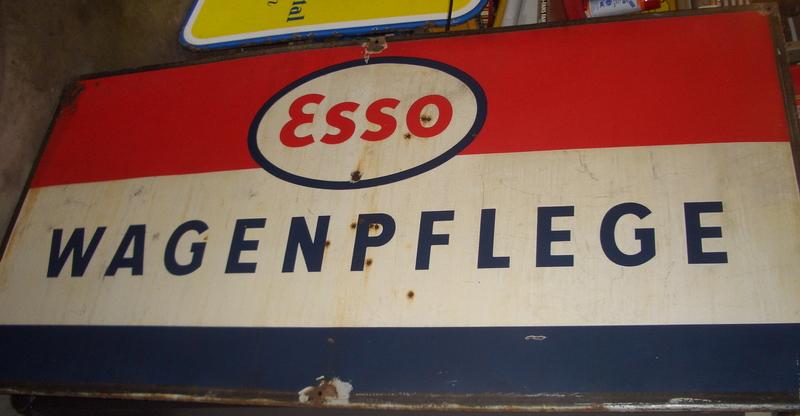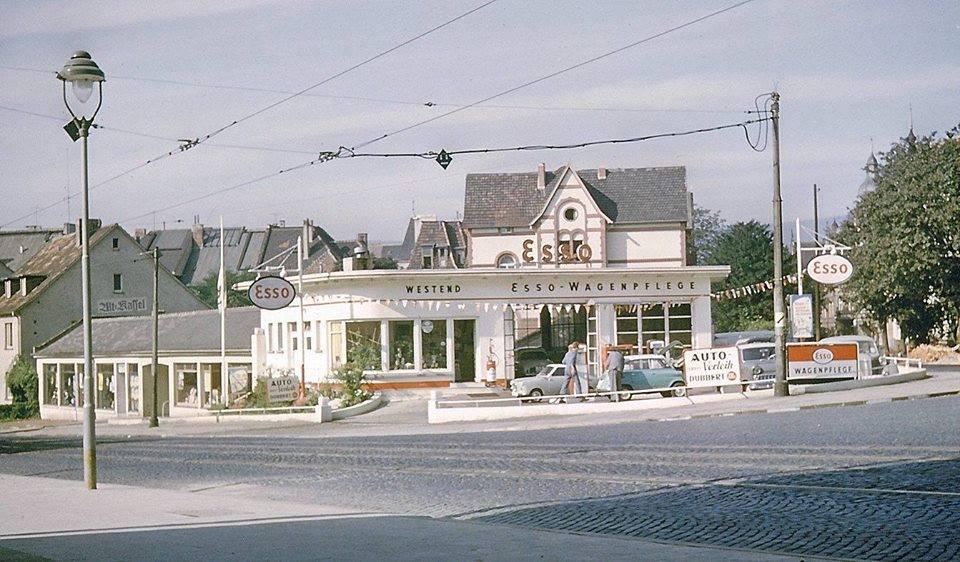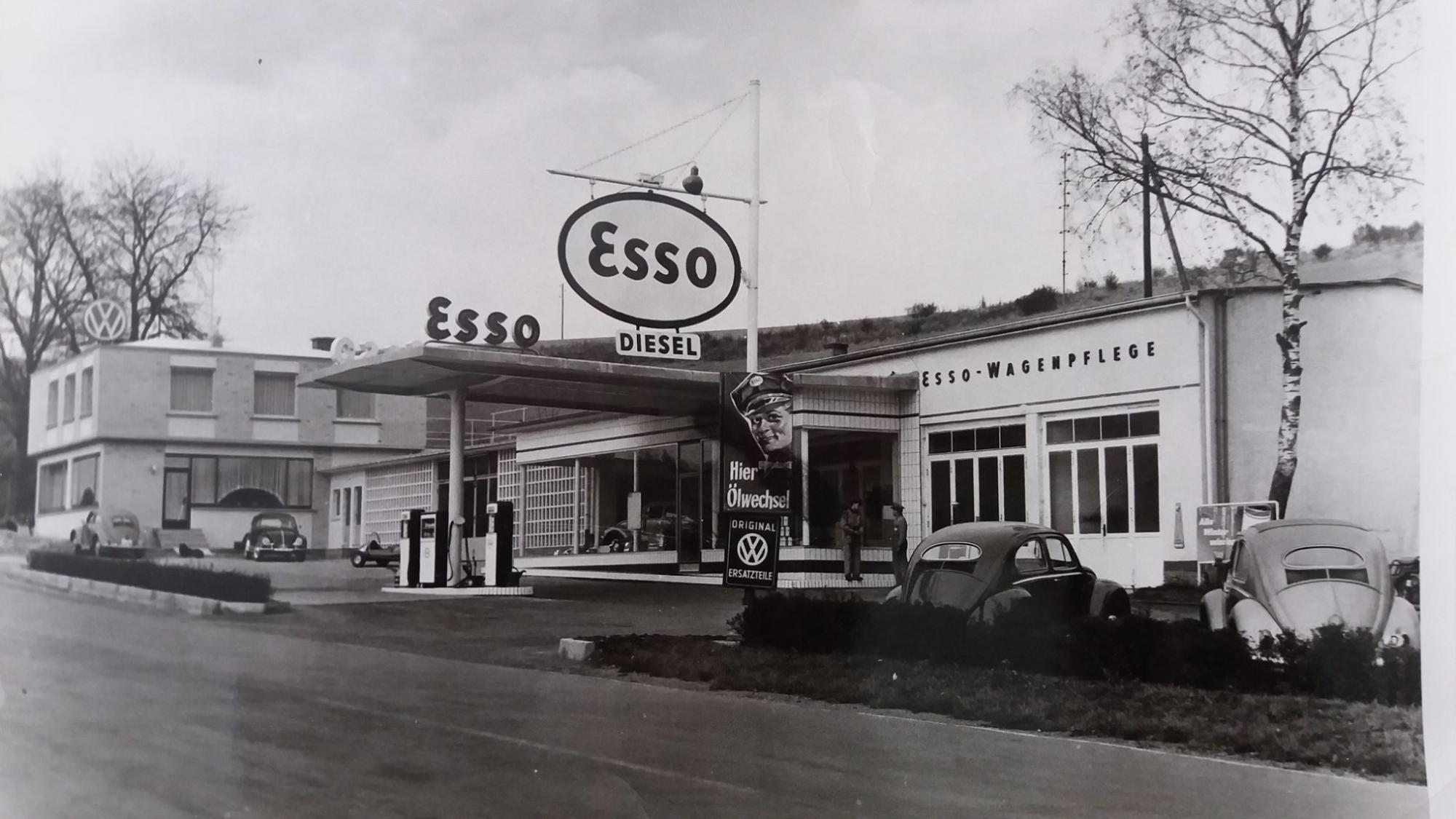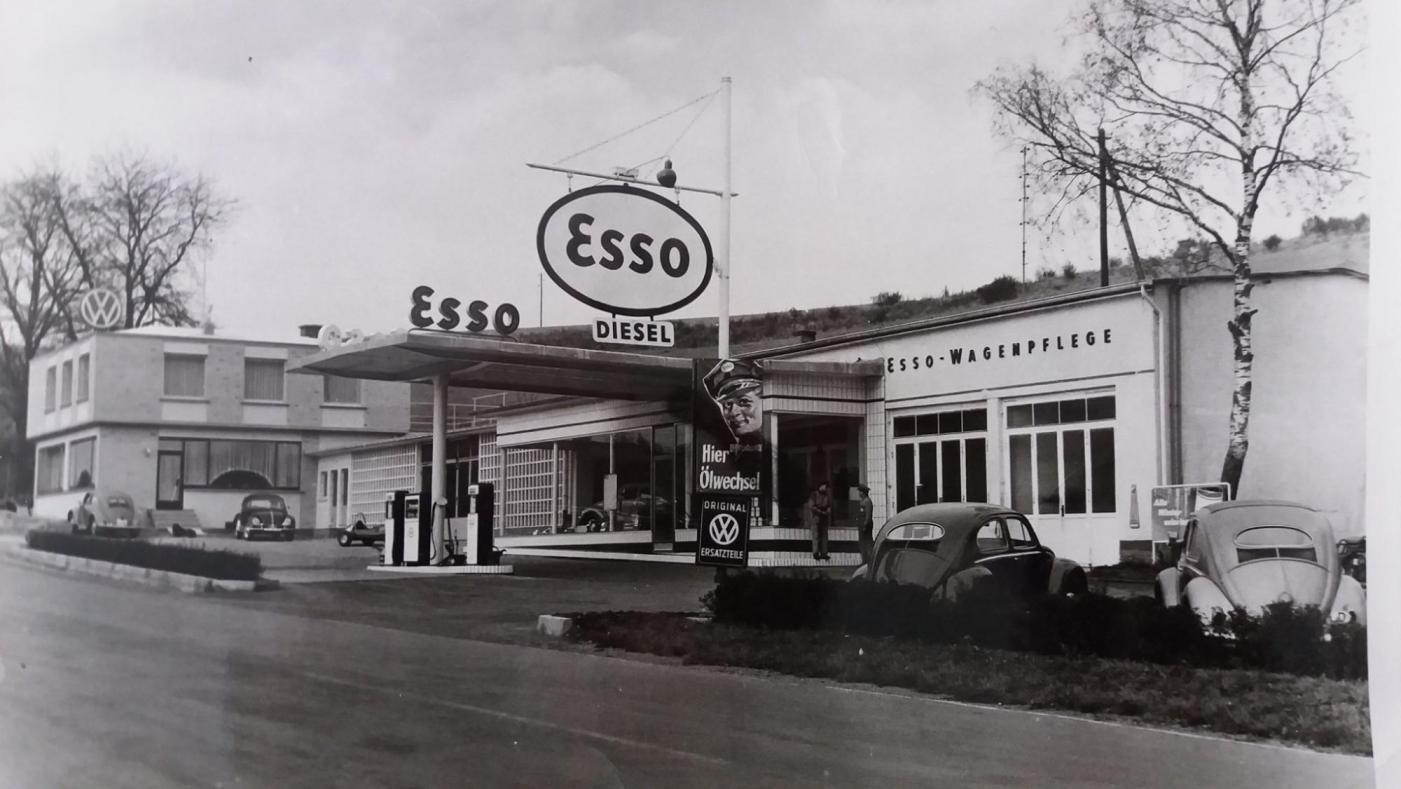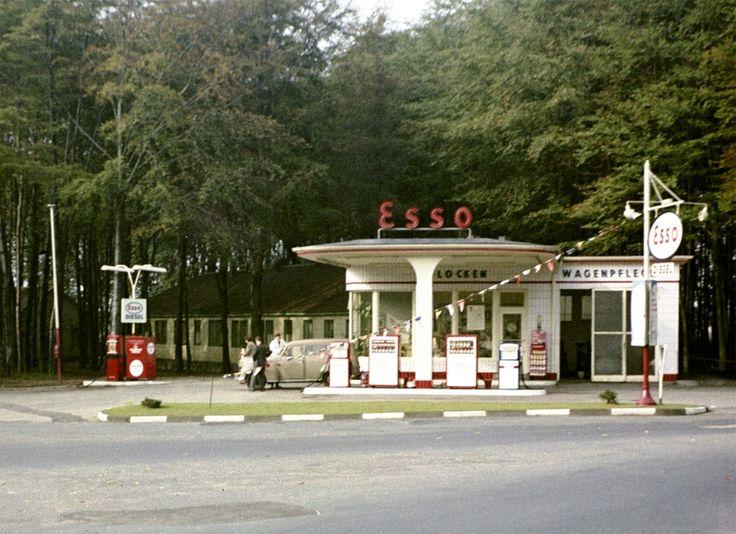
Suche die Schriftart, die u.a. in den 1950er Jahren an "ESSO"-Tankstellen verwendet wurde.
Suche die Schriftart, mit welcher Namen der Betreiber sowie Beschriftungen von Eingängen wie z.B. "Wagenpflege", von außen an den ESSO-Tankstellen angebracht wurden. Ich wünsche mir Hinweise zu der Schriftart, die in den 1950er Jahre bis in die 1960er Jahre hinein verwendet wurde.
Ich weiß es nicht, hab aber besser erkennbare Bilder gefunden:
Hab’s entzerrt:
Der wesentliche Hinweis ist, dass so etwas in der vordigitalen Zeit nicht mit Schriftarten in heutigem Sinne gemacht wurde. Erklärt wird das hier: https://www.typografie.info/3/artikel.htm/wissen/warum-nicht-hinter-allen-buchstaben-fonts-stecken-r413/
Dann werde ich weiter schauen ob ich eine vergleichbare Schrifttype finde.